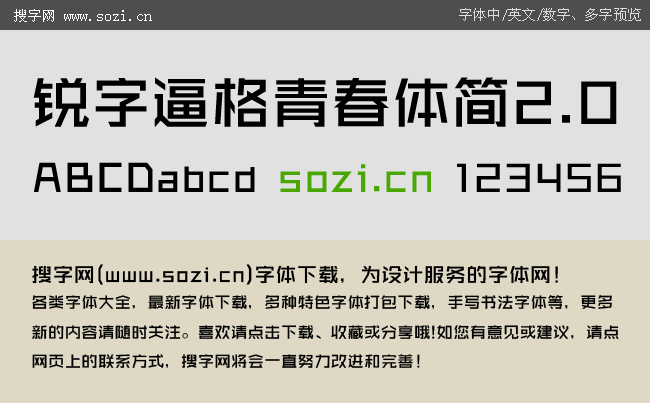
銳字逼格青春粗黑體簡(jiǎn)2.0
搜字網(wǎng)提供一款銳字逼格青春粗黑體簡(jiǎn)2.0中文字體下載,銳字逼格青春體是一款應(yīng)用于設(shè)計(jì)方面的中文簡(jiǎn)體漢字,該字體端正大方,擁有卡通風(fēng)格,整體效果非常出眾,并且字庫完整,可以應(yīng)用于廣告設(shè)計(jì)、名片設(shè)計(jì)、包裝印刷、產(chǎn)品設(shè)計(jì)等應(yīng)用。